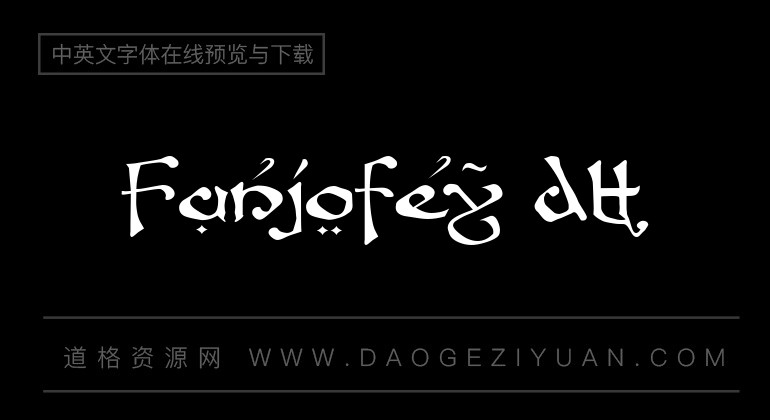
Fanjofey AH
Fanjofey AH是由佛罗伦萨设计师Alessandro Segalini设计的一款层次丰富的艺术字体。它具有极其流畅的笔画,以及大量不同风格的字形,可以满足多种设计需求。它可以用来创建复古、古典、现代等多种风格的标题和文本,并且可以提供多种字重和字体大小,以及多种字形组合,可以满足不同的设计需求。
Fanjofey AH是一款非常不错的手写艺术字体,具有很好的视觉感,适合于文化类的宣传设计、商业类品牌的广告和产品包装设计以及个性化文字排版等较多场景。